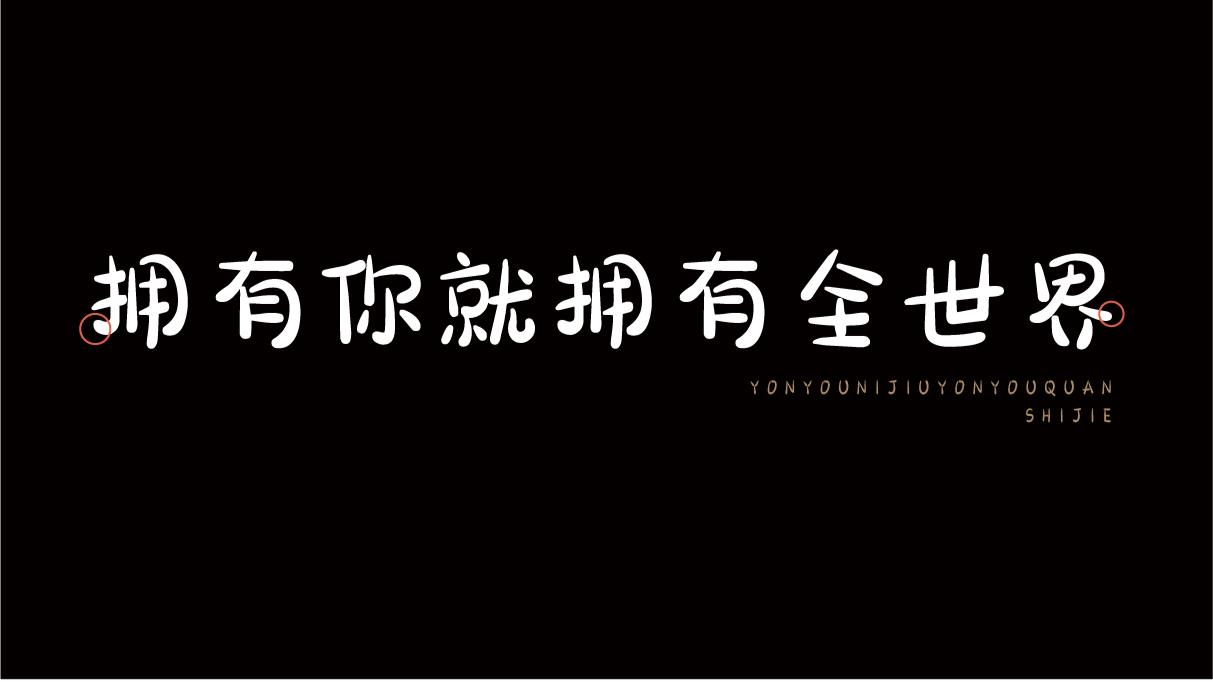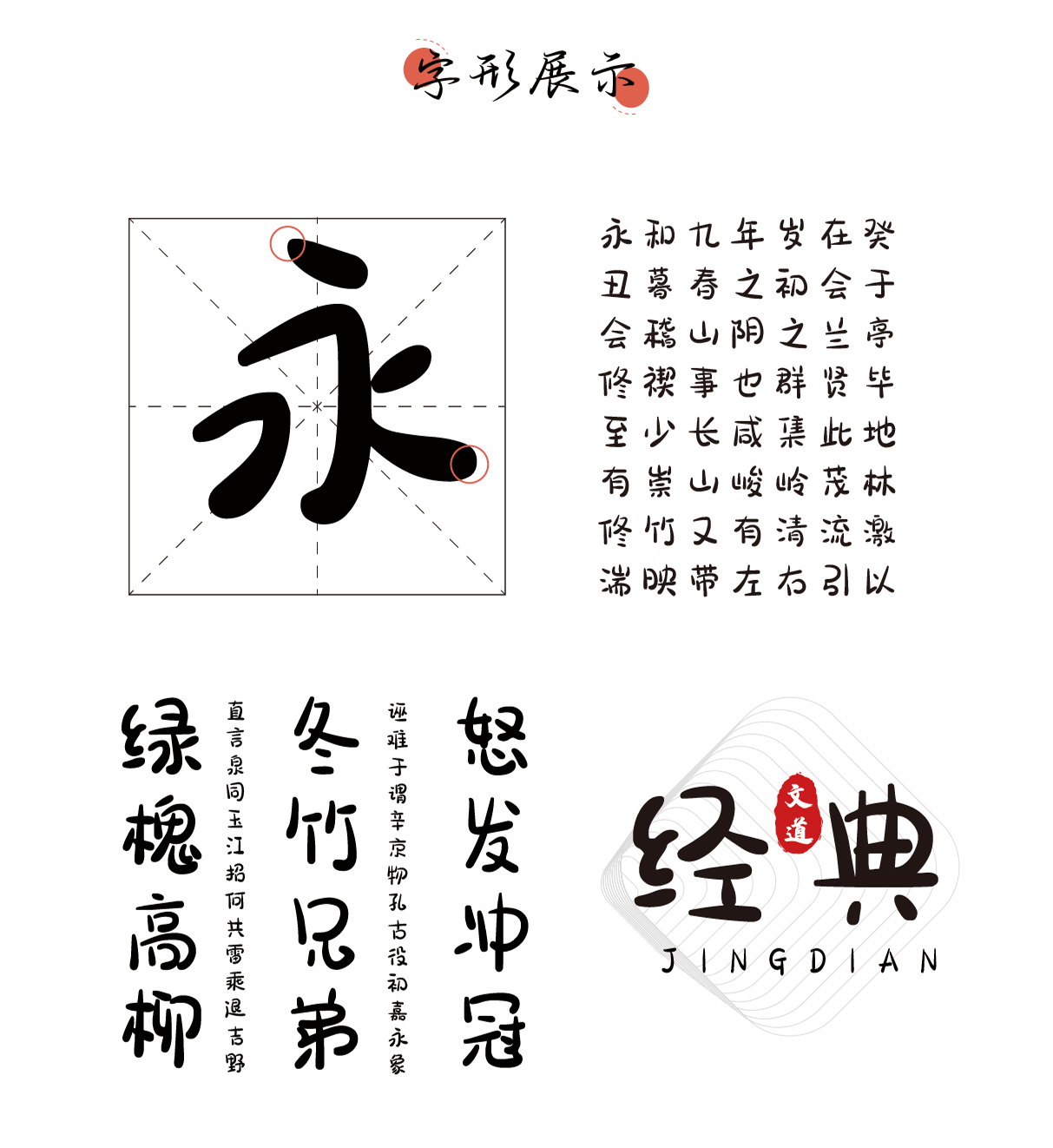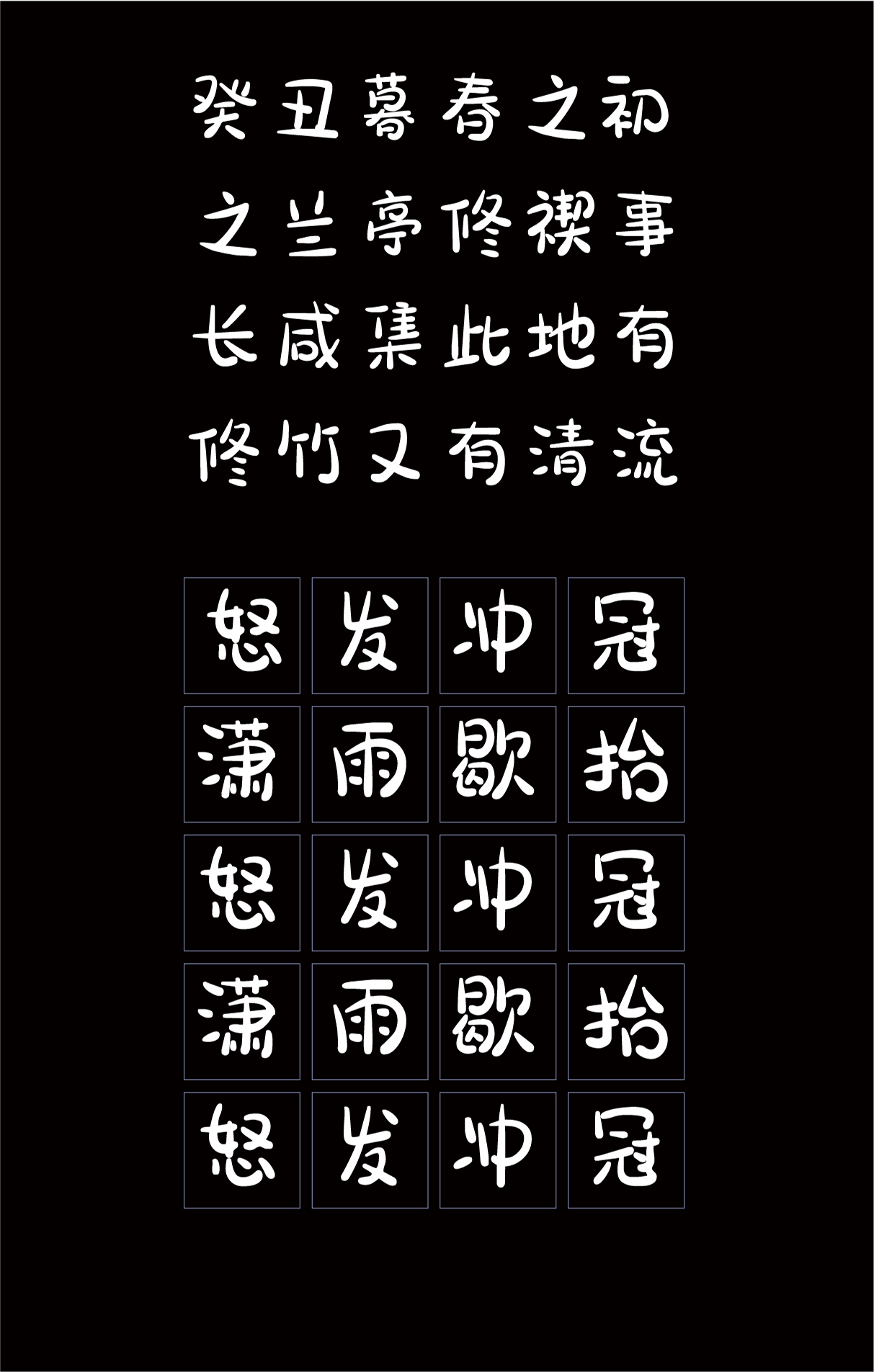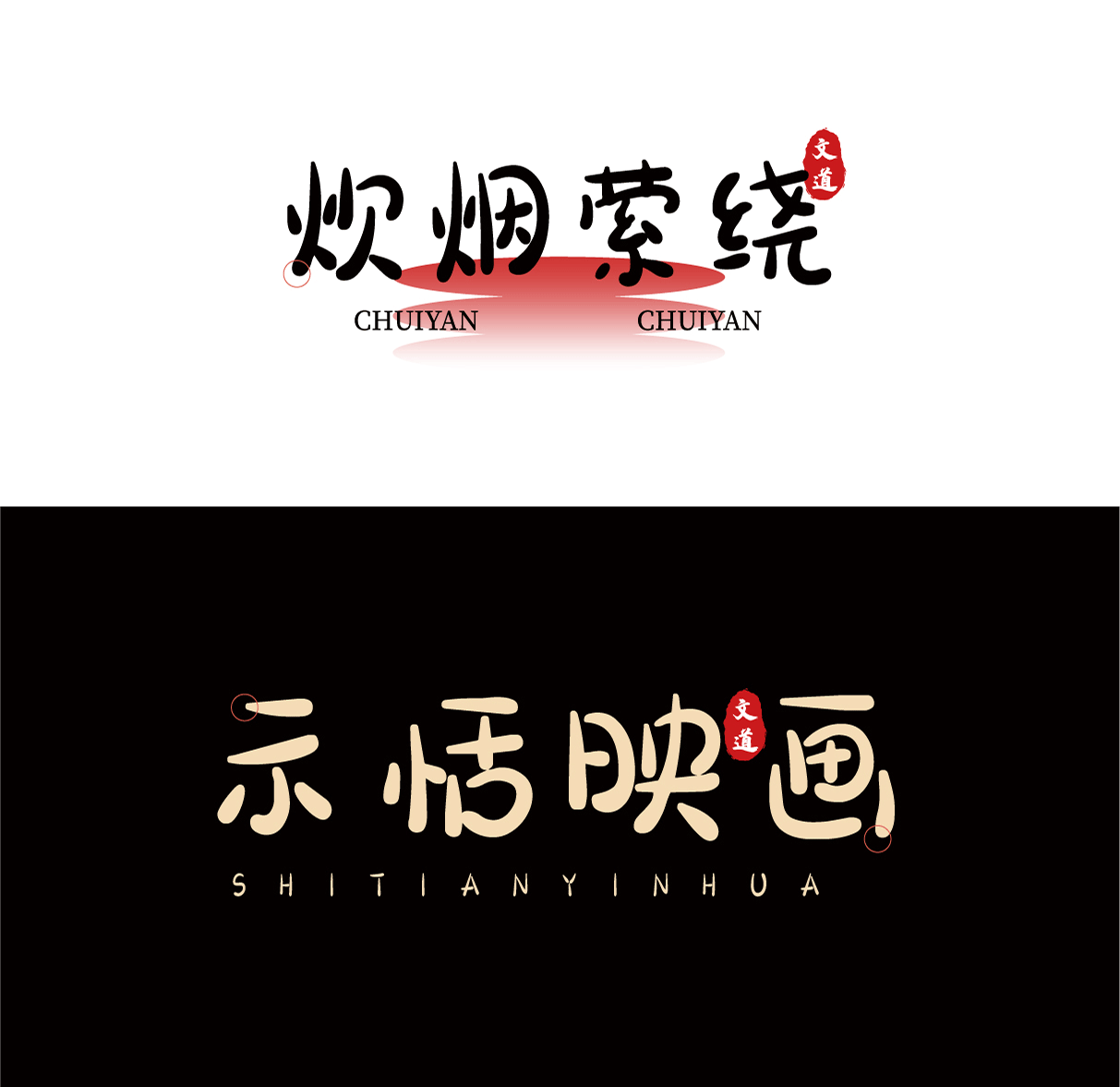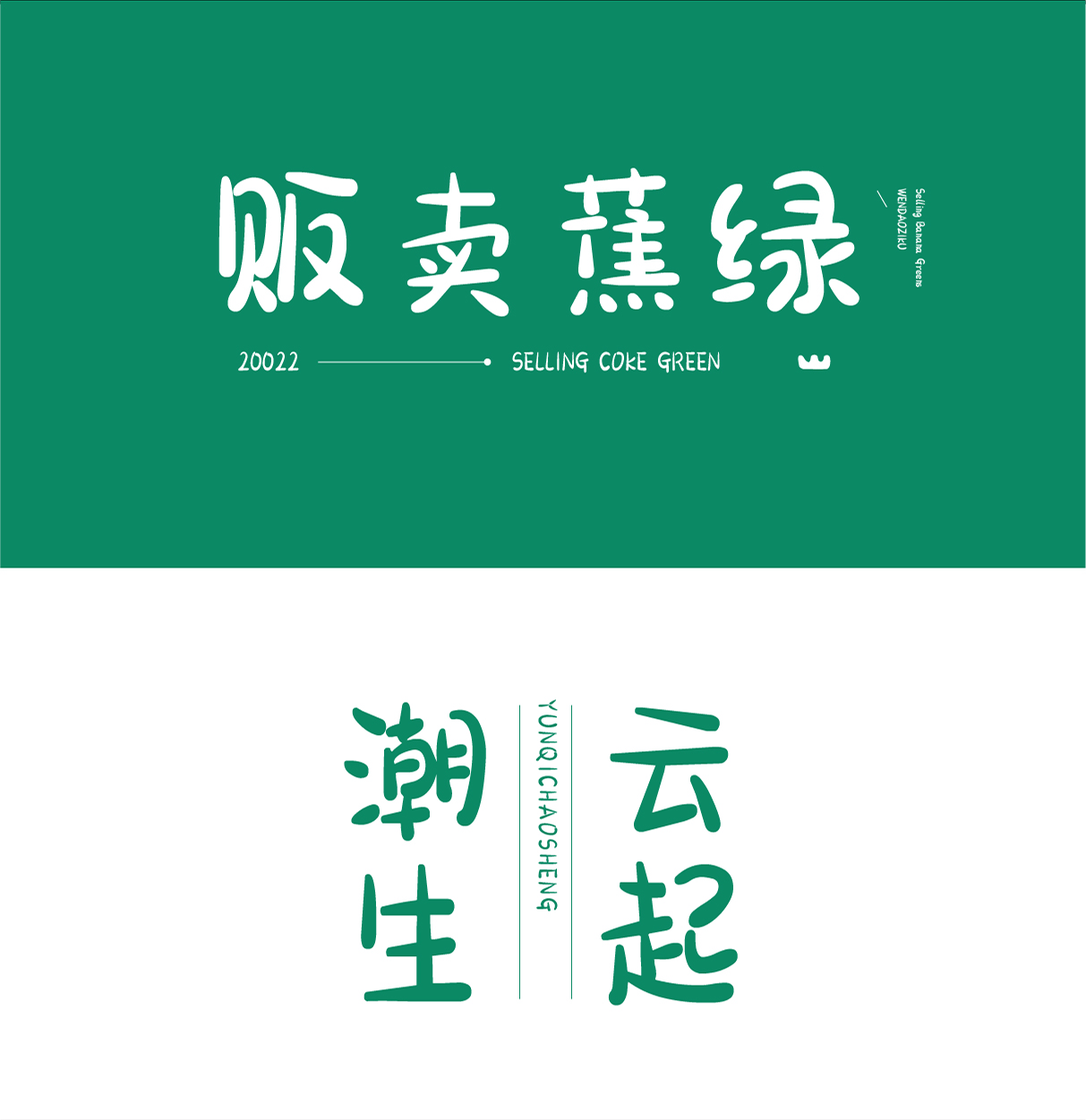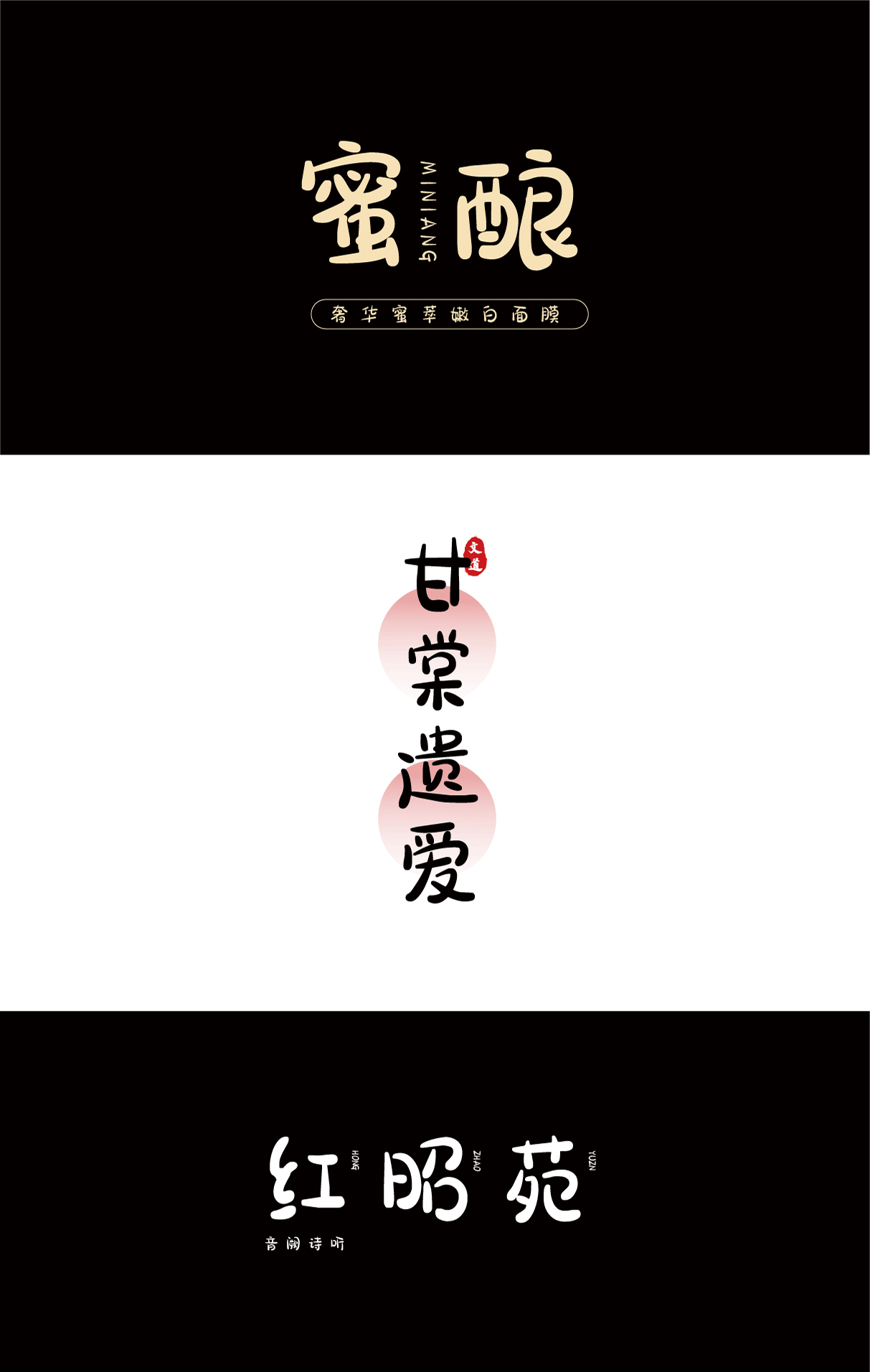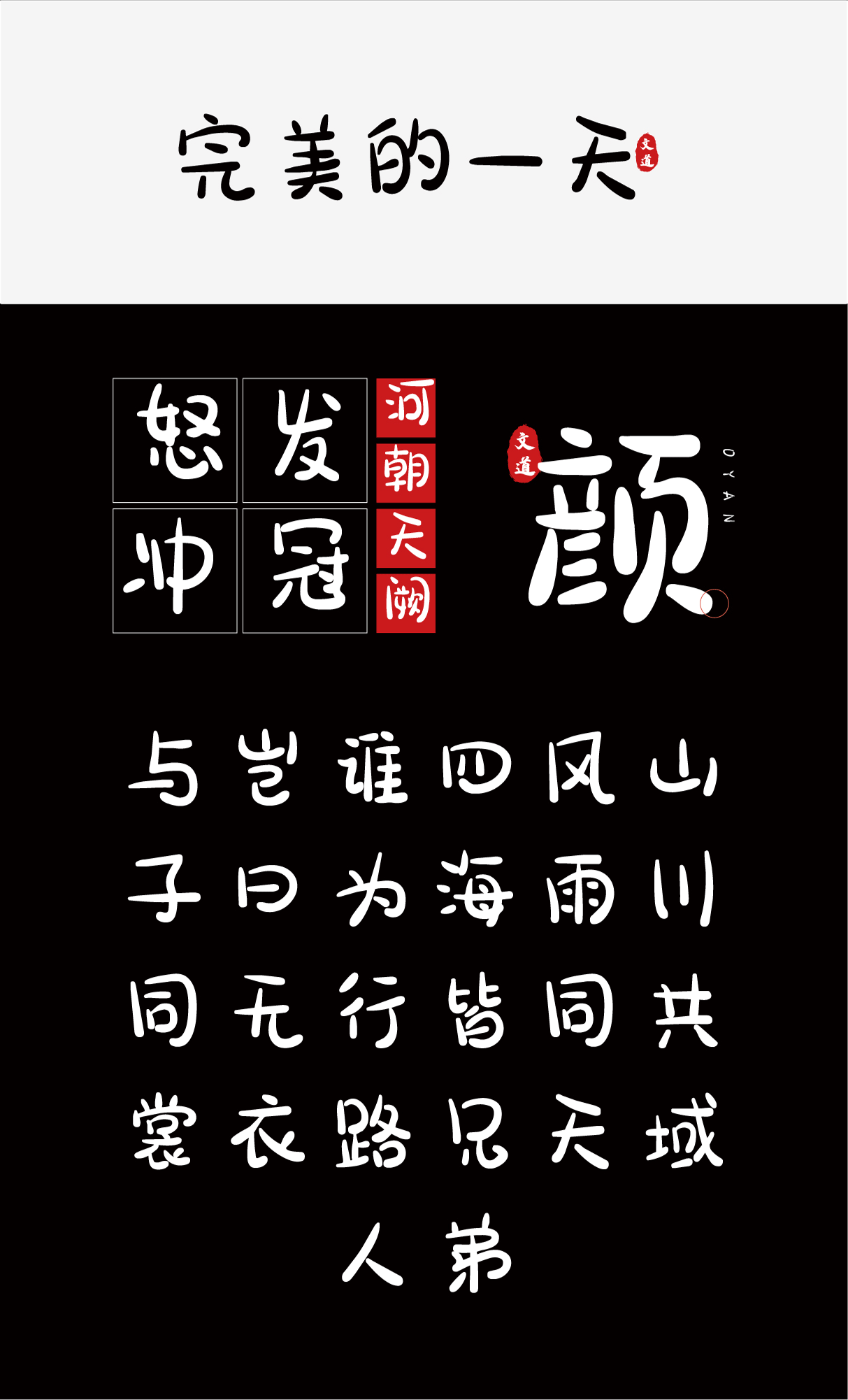
| 字体名称: | 拥有你就拥有全世界 |
| 所属分类: | 创意体 可爱 手写 |
| 简介: | 拥有你就拥有全世界是一款带有书法味道的纯手写字体,字型偏圆,笔画中也减少了过多的处理和笔势,厚重、饱满。因为是纯手写的原因,它独特的气质更与其他字体不同,看似统一,其实各有各的味道,每个字都可以独具风情。字由字在,大到自然,便是对它最好的诠释。 |